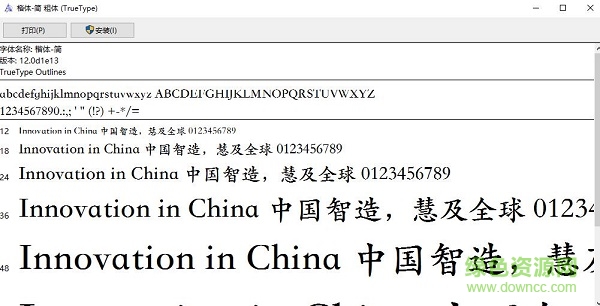
軟件介紹 軟件標(biāo)簽: 楷體字體 粗體字體 楷體-簡 粗體是一款生動鮮活的中文楷書字體,橫平豎直,結(jié)構(gòu)規(guī)范統(tǒng)一,整體簡約美觀,具有獨特氣質(zhì)的氣質(zhì),閱讀效果極佳,歡迎需要的朋友在本站免費下載!楷書字體發(fā)展歷程楷書的萌芽期——秦漢,楷書發(fā)展期——魏、晉、南北朝,楷書繁榮期——隋、唐、五代,楷書守成期——宋、元、明、清。楷體字體推薦標(biāo)準(zhǔn)楷體字庫 ttf授權(quán):免費軟件 WinAll, WinXP, Win7大?。?.4M語言:中文標(biāo)準(zhǔn)楷體簡字體是一款采用國家標(biāo)準(zhǔn)字符集的楷書字體,該字體結(jié)構(gòu)工整,線條過渡平穩(wěn),風(fēng)格質(zhì)樸,和范本一樣規(guī)矩方正,需要這款字體的小伙伴快來綠色資源網(wǎng)下載吧!GB2312字符集區(qū)位碼介紹01-09區(qū)為特殊符號。16-下載地址楷體粗體ttf字體安裝方法方法一:控制面板/字體/文件/安裝新字體;方法二:直接將字體復(fù)制到C:\WINDOWS\Fonts。方法三:針對win7系統(tǒng),用戶只需選中字體右鍵安裝即可。 軟件截圖 上一張下一張(1 / 1) 安裝詳細截圖 猜你喜歡 楷書字體 楷書字體 楷書字體是綠色資源網(wǎng)小編專為大家收集的一類非常流行而且好用的楷書字體,它包括了各種形式的楷書??瑫步姓⒄鏁?、正書。從程邈創(chuàng)立的隸書逐漸演變而來,更趨簡化,橫平豎直,筆勢雄奇,姿態(tài)橫生,可應(yīng)用于繪畫設(shè)計、藝術(shù)創(chuàng)作、平面廣告、印刷包裝、電視廣告等等各行各業(yè)。也是現(xiàn)在很多行業(yè)必用的一類字體,小編收集的這一類楷書字體希望能更好的幫助大家收集和使用楷書字體。 查看更多>> 楷體國標(biāo)字體官方版 2.45M/中文/7.1/下載 漢儀閃耀楷書字體 1.77M/中文/0.0/下載 華為漢儀錦時楷書 2.92M/中文/5.0/下載 楷書字典手機版 4.46M/中文/5.0/v2.0 安卓版下載 經(jīng)典楷體繁體 3.96M/中文/5.0/下載 楷書繁體字體包 9.76M/中文/8.0/下載 其他版本下載 標(biāo)題 大小 更新日期 下載 下載地址 電腦版 楷體粗體 點擊報錯 軟件無法下載或下載后無法使用,請點擊報錯,謝謝! 關(guān)閉報錯反饋 請描述您所遇到的錯誤,我們將盡快予以修正,謝謝! *必填項,請輸入內(nèi)容 本類最新 dreamweaver字體庫 首爾南山體字體 v1.06 官方版 潮字社風(fēng)云簡ttf 潮字社凌渡鯤鵬簡體字體 潮字社曾玉波手書簡字體 微博慧心字體 用戶評論 熱門評論 最新評論 發(fā)表評論 查看所有評論(0) 昵稱: 請不要評論無意義或臟話,我們所有評論會有人工審核. 字數(shù): 0/500 (您的評論需要經(jīng)過審核才能顯示)